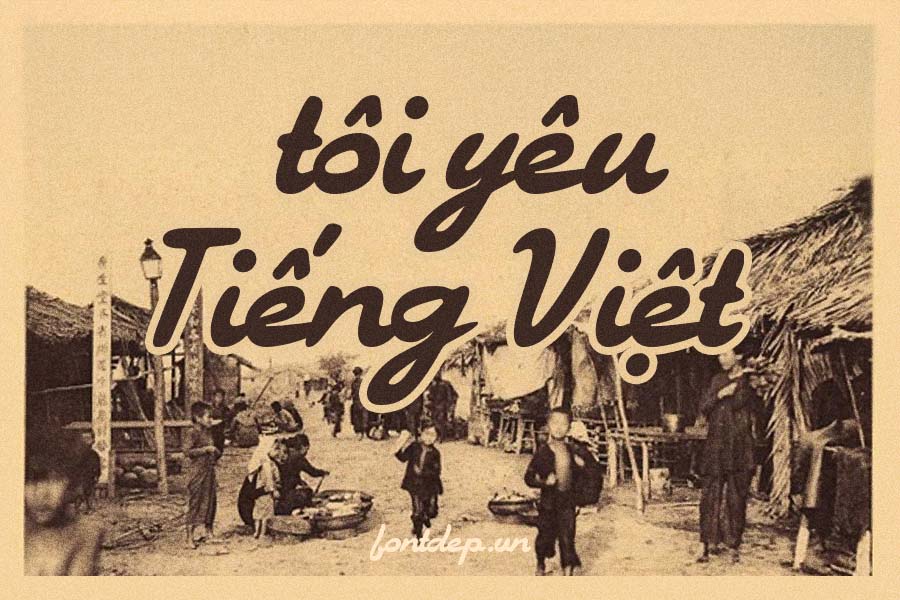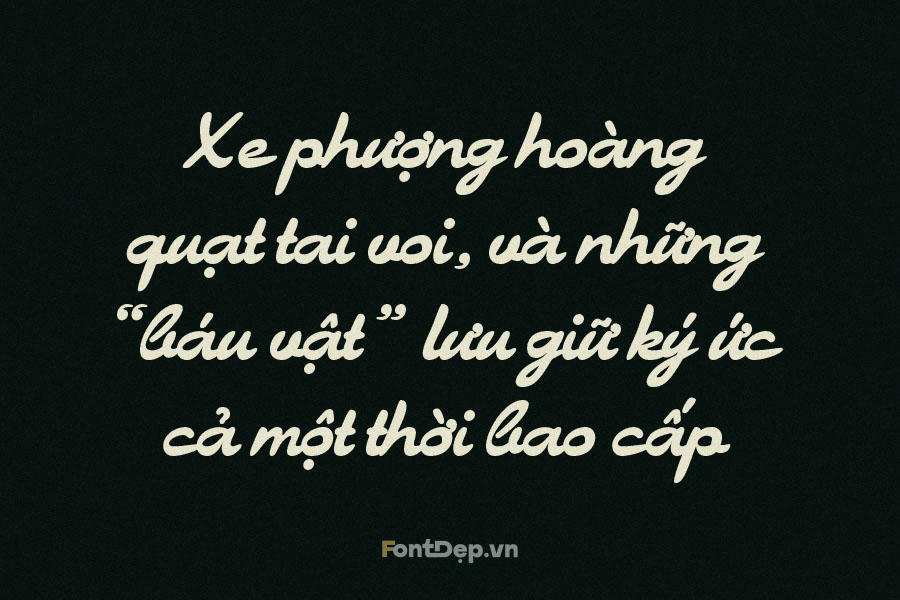
Font Chữ TH Bonitte – Kiểu Chữ Script Retro, Viết Tay Việt Hóa
Tác giả Marvadesign
Nếu bạn đang tìm một font chữ script mang đậm nét cổ điển nhưng vẫn linh hoạt trong ứng dụng hiện đại, thì TH Bonitte chính là lựa chọn đáng cân nhắc. Đây là bộ font chữ viết tay do Marvadesign sáng tạo (2025) và đã được Phạm Sơn Việt hóa, giúp hỗ trợ đầy đủ tiếng Việt một cách chuẩn xác, mượt mà và dễ sử dụng.
Font Chữ Bonitte – Script Retro, Viết Tay Mượt Mà & Việt Hóa Bởi Phạm Sơn
Đặc điểm nổi bật của TH Bonitte
Font Bonitte được thiết kế theo phong cách script retro, lấy cảm hứng từ những đường bút lượn mềm mại, uyển chuyển nhưng vẫn có sự dày dặn, chắc chắn. Bộ font này bao gồm hơn 400 glyphs cùng hệ thống ligature và alternate đa dạng, cho phép bạn tùy biến chữ viết với nhiều phong cách khác nhau. Nhờ vậy, Bonitte có thể mang đến sự độc đáo và mới lạ cho mỗi thiết kế, dù là trong logo, poster hay bao bì sản phẩm.
Điểm đặc biệt của Bonitte là sự cân bằng giữa sự cổ điển và tính hiện đại. Các đường nét mang hơi thở vintage, retro nhưng được xử lý tinh tế để dễ dàng áp dụng vào nhiều thiết kế sáng tạo ngày nay. Font chữ không chỉ tạo cảm giác thủ công, gần gũi mà còn giữ được sự chuyên nghiệp, sang trọng.
Ứng dụng trong thiết kế
Với sự Việt hóa hoàn chỉnh bởi Phạm Sơn, TH Bonitte trở thành một font chữ Việt hóa cực kỳ hữu ích cho các nhà thiết kế tại Việt Nam. Font phù hợp để ứng dụng trong nhiều dự án như:
• Thiết kế logo thương hiệu, đặc biệt trong ngành thực phẩm, đồ uống, craft beer.
• Poster sự kiện, lễ hội mang phong cách hoài cổ.
• Bao bì sản phẩm handmade, organic cần sự gần gũi và tinh tế.
• Thiết kế ấn phẩm nội thất, thời trang hoặc các dự án branding cá tính.
TH Bonitte là một font chữ viết tay retro đẹp mắt, vừa mang sự phóng khoáng nghệ thuật, vừa đảm bảo tính ứng dụng cao. Với phiên bản Việt hóa bởi Phạm Sơn, đây chắc chắn sẽ là công cụ mạnh mẽ giúp bạn nâng tầm thiết kế, tạo nên những sản phẩm ấn tượng và khác biệt.